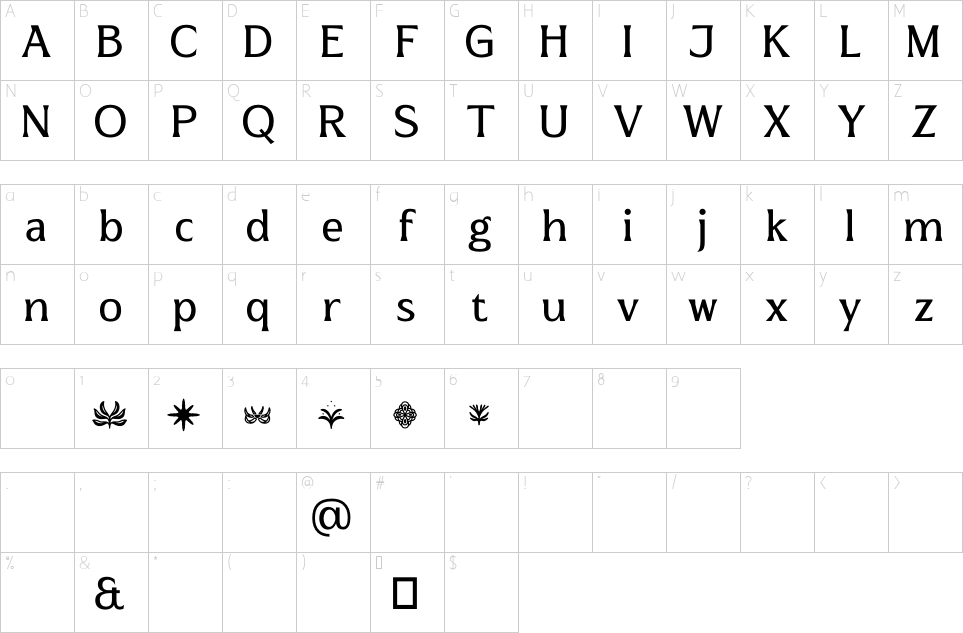
Macala De Club é uma elegante fonte gráfica que destaca-se por sua elegância e sofisticação. Criada por Putu Dody Permana, esta fonte tem uma aparência minimalista e perfeita para projetos que exigem um toque moderno e sofisticado. Com seus suportes completos para Windows e Mac, a Macala De Club é uma opção versátil que pode ser facilmente integrada em qualquer projeto de design digital. Com seu design cuidadosamente pensado, Macala De Club oferece uma solução que combina perfeitamente com o estilo moderno de muitos projetos de design gráfico. Seja você um designer de web, um criador de conteúdo digital ou simplesmente alguém interessado em aprimorar seus projetos de design, Macala De Club é uma fonte que vale a pena explorar. Download esta fonte livre hoje e experimente sua beleza única.